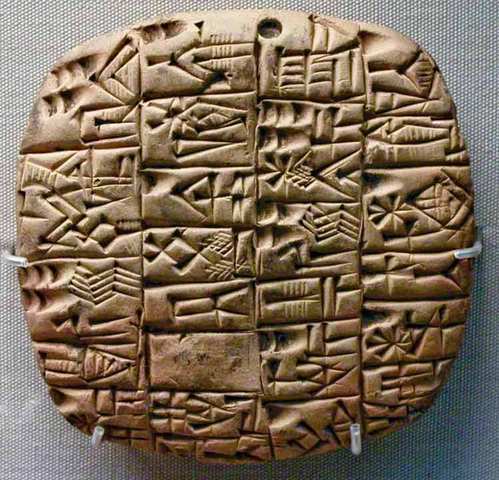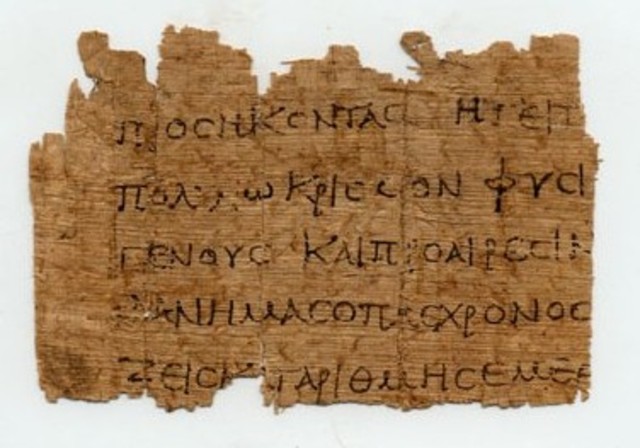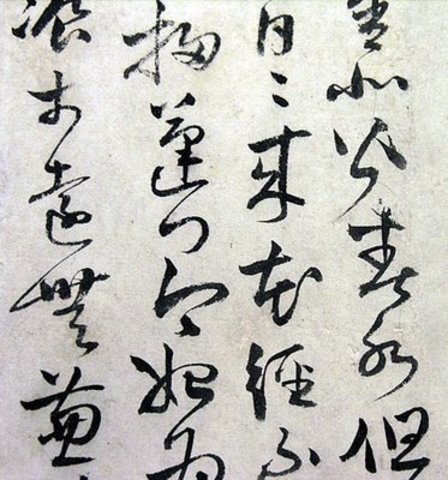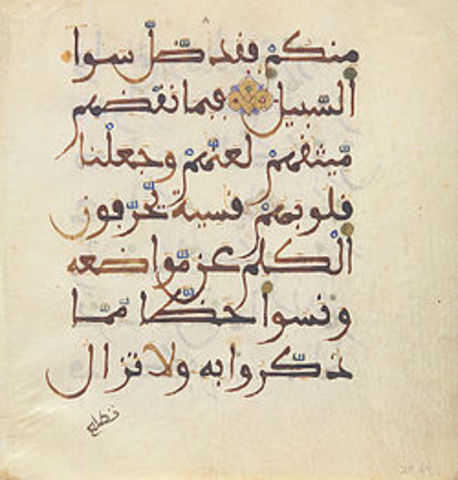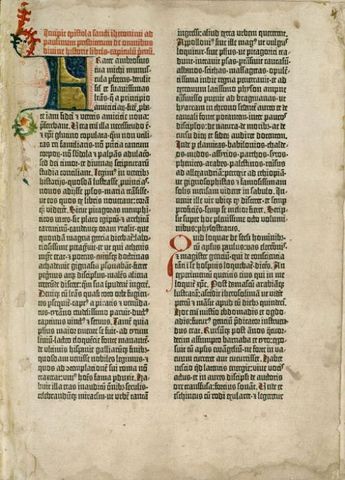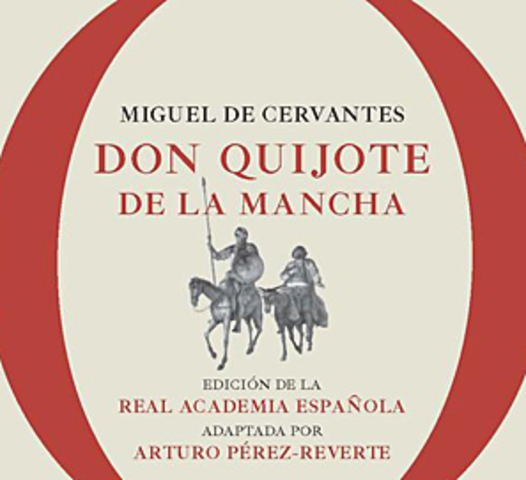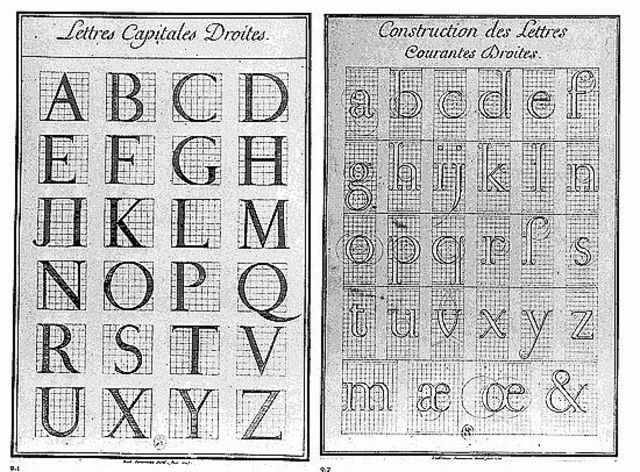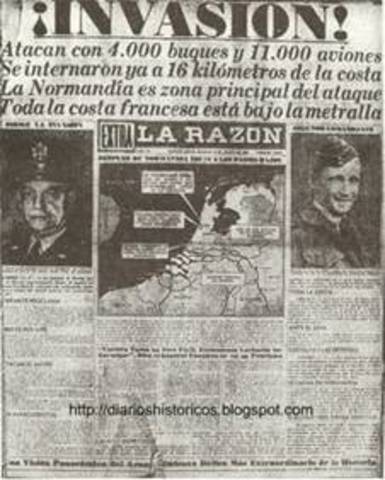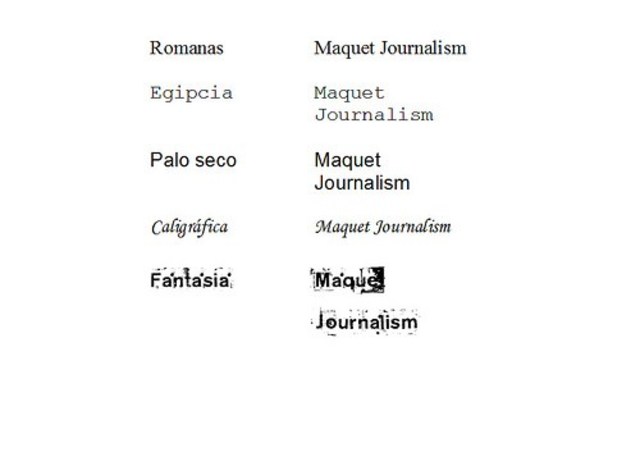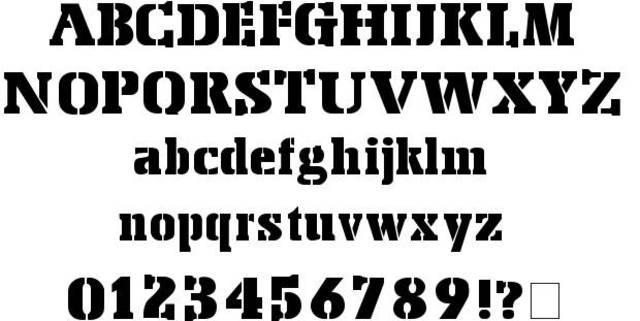
La caligrafia nace a partir de la necesidad del ser humano y las civilizaciones de inmortalizar su pensamiento y sus ideas. Nace aproximadamente 3500 años a. de C. con Tablillas pictográficas de Mesopotamia y los Primeros caracteres chinos grabados.
La escritura no tardó en trasformarse en un arte con entidad propia. Evolución de los materiales asociada a la constante búsqueda de nuevos caracteres cada vez más sencillos y accesibles.
Se dice que la caligrafía china es la mas antigua de la escritura existente hoy en día. Ésta se fundamenta en la belleza visual de los ideogramas, la técnica de su realización y los preceptos metafísicos de la cultura tradicional china.
Es la caligrafía basada en el empleo del alfabeto latino, creado por los Romanos, con el que en la Edad Media escribían los monjes copistas sobre pergamino. Es un alfabeto que constaba únicamente de las que hoy llamamos letras mayúsculas. La caligrafía mas importante fue la ROMANA IMPERIAL INCISA.
Aproximadamente a la misma fecha la cultura islámica crea su propia caligrafía basada en el alfabeto árabe. se considera como la principal arte de la cultura islámica.
En pleno Renacimiento, con la invencion de la imprenta por ohannes Gutenberg, se hicieron los primeros impresos como "la Biblia de 42 líneas" los cuales utilizaron un estilo de letra del período gótico y el tipo de letra redonda o romana.
La famosa "textura" de Gutenberg fue suplantada por formas cursivas como la Fraktur y Schwabacher. en este estilo se hizo la impresión de libros como la Biblia del Rey James y el Quijote de la Mancha de Miguel de Cervantes. Debido a esto, se vio la necesidad de crear nuevos formatos tipográficos llevaran al arte de crear letras a un nuevo nivel.
Tal fue la importancia de la tipografía, que en 1692 el rey Luis XIV ordenó la creación de un comité de eruditos para la creación de un nuevo tipo que fuera diseñado bajo principios científicos, con concepto racional, con letras de perfecto eje vertical y serifas simétricamente horizontales
Hasta esta fecha se hicieron muchos avances técnicos, se hicieron mejoras en las piezas fundidas y en los ajustes de los tipos; la superficie del papel fue más consistente y se elaboraron tintas de mayor calidad que dieron como resultado una impresión superior.Todo esto antes de la Era industrial.
La llegada de la Era Industrial supuso un cambio dramático, ya que se cambiaron los delicados tipos artísticos del pasado y tuvieron los tipos mecánicos, gruesos y rígidos. Estos usados mas que todo para titulares de periódicos con el fin de llamar mas la atención y ser mas contundentes.
Al estar la imprenta en toda Europa para este siglo se establecieron cinco tipos de letra, los cinco grandes tipos de familias tipográficas son las romanas, egipcias, palo seco, cursiva o caligráfica y los tipos de fantasía.
Se dice que en el sigo XX se vvio una revolución tipográfica cuando Theodore Low De Vinne mandó a realizar a finales del siglo XIX un tipo especial para la impresión de la revista Century. Fue el primero diseñado especialmente para una publicación. Desde entonces se busca crear una tipografía especial para cada concepto y diseño.
Posteriormente con la industria de los medios de comunicación impresos, se maduraron los tipos de letra mas conocidos como lo son: Arial, Times, Avant Garde, Futura, Trade Gotic, Palatino, Memphis, Beton, Cairo, Karnak, Garamond, Helvetica, etcétera.
El rápido crecimiento de la televisión y los avances de la tecnología tipográfica ayudaron a una reinvención de la naturaleza de la tipografía; además, los cambios científicos, sociales y políticos de los años sesenta tuvieron un reflejo inmediato sobre la tipografía.
las computadoras y sistemas informáticos los que cambiaron todo, la litografía basada en de metal fundido comienza a desaparecer, de metal fundido comenzaran a desaparecer. Apple Macintosh en 1982 fue el primer sistema operativo que mostraba diferentes tipos de letra para elegir y aplicar en las hojas de texto, lo cual fue una revolución.
Las computadoras incitaron a los diseñadores a pedir más y más tipos de letras para cubrir sus inspiraciones creativas y los programas de diseño. Con la llegada de Internet, la tipografía y sus miles de creaciones pasaron a un nuevo cambio, la web, desde donde continúan sus constantes cambios.